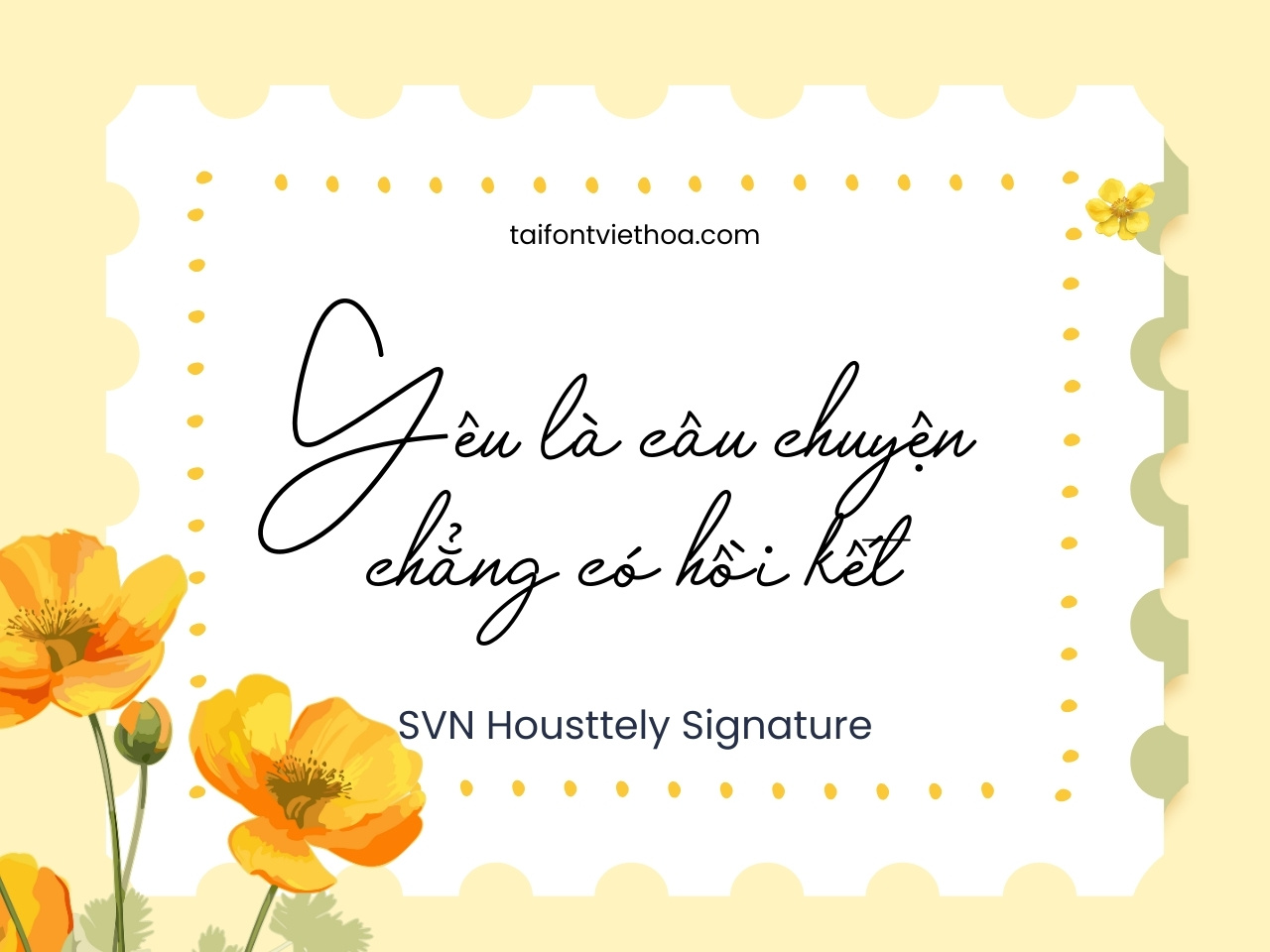
Giới thiệu về font SVN Housttely Signature – Kiểu chữ chữ ký viết tay mềm mại và sang trọng
SVN Housttely Signature là phiên bản Việt hóa của font Housttely Signature – một kiểu chữ viết tay mang phong cách chữ ký cá nhân, mềm mại và thanh lịch. Font được thiết kế nhằm tạo ra sự tự nhiên, gần gũi và tinh tế, rất phù hợp cho các dự án thiết kế thương hiệu cá nhân, thiệp mời, lời chúc và các sản phẩm sáng tạo mang phong cách sang trọng và độc đáo.
Phiên bản Việt hóa của SVN Housttely Signature đã được Taifontviethoa.com chăm chút kỹ lưỡng, hỗ trợ đầy đủ dấu tiếng Việt cùng hơn 60 ngôn ngữ khác. Font giữ nguyên nét mềm mại, uyển chuyển và tự nhiên của bản gốc, giúp các nhà thiết kế dễ dàng áp dụng trong các dự án sáng tạo mang dấu ấn cá nhân và sự tinh tế.
Thiết kế chữ ký uyển chuyển – Lý tưởng cho thương hiệu cá nhân và thiết kế thiệp
SVN Housttely Signature sở hữu các nét chữ mềm mại, thanh thoát với độ nghiêng nhẹ nhàng và các ligature tinh tế tạo nên sự hài hòa và tự nhiên trong tổng thể thiết kế. Font mang lại cảm giác sang trọng, duyên dáng và rất phù hợp cho tiêu đề, logo, bao bì hoặc các phần thiết kế cần điểm nhấn mềm mại và cá nhân hóa.
Ứng dụng lý tưởng: thiết kế thương hiệu cá nhân, thiệp cưới, thiệp mời, lời chúc, logo thời trang, bao bì mỹ phẩm và các dự án sáng tạo cần sự sang trọng, tinh tế và độc đáo. Ngành nghề phù hợp: thời trang, mỹ phẩm, nghệ thuật, truyền thông sáng tạo và các thương hiệu định vị theo phong cách thanh lịch, duyên dáng.